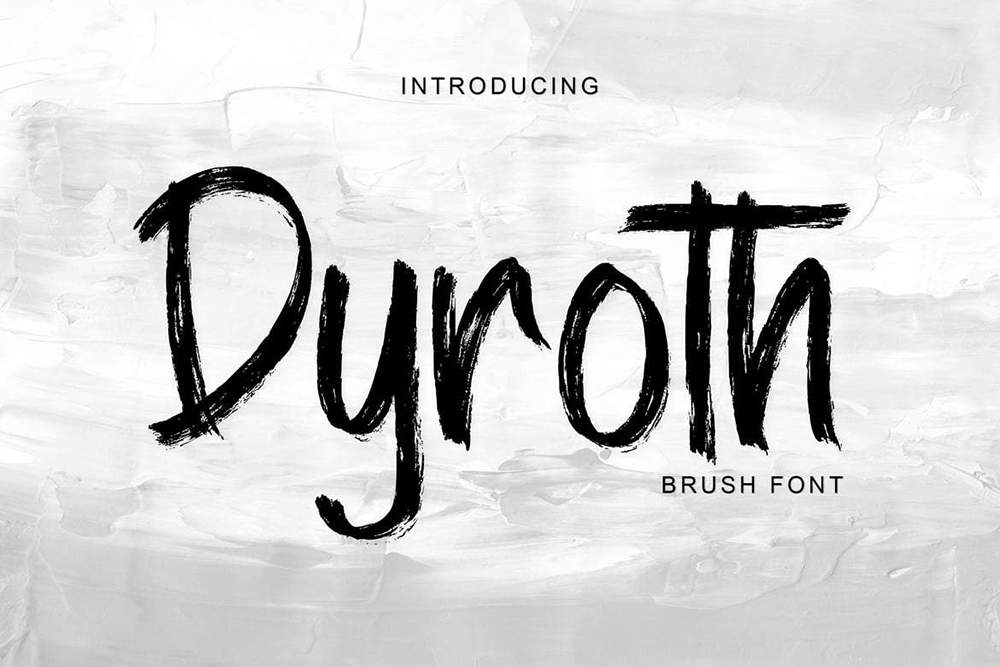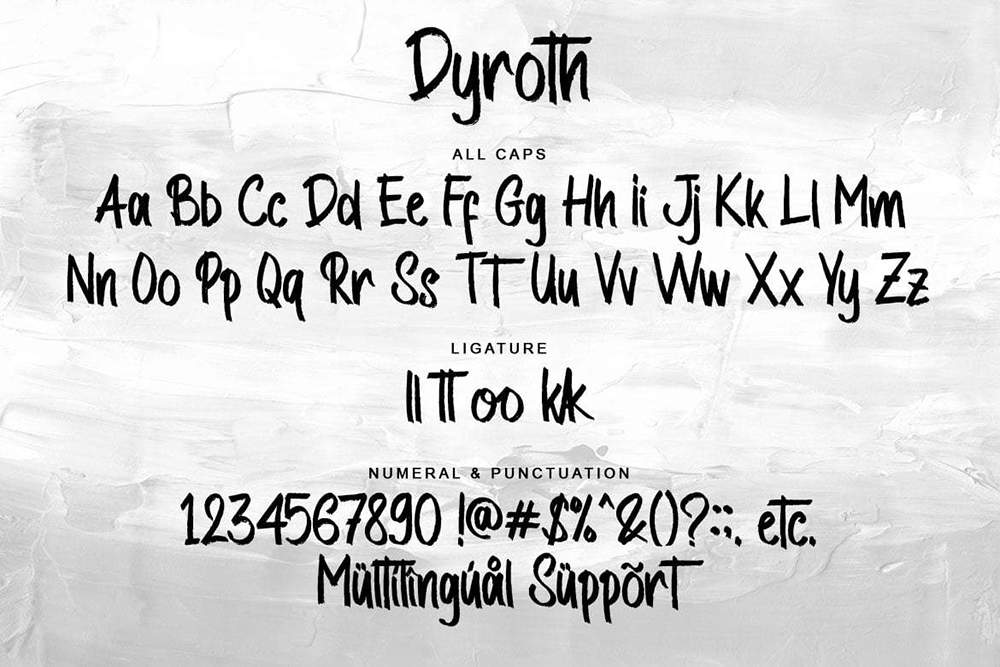
فونت پرمیوم و انگلیسی Dyroth Font یک فونت قلممو است که با حروف بزرگ و کوچک استاندارد، اعداد، علائم نگارشی، لیگاتور و پشتیبانی چندزبانه ارائه میشود. فونت Dyroth بهترین انتخاب برای برندسازی، لوگو، ماکت تیشرت، تبلیغات دیجیتال، نقل قول و غیره است. این فونت برای تمام نیازهای طراحی شما بهترین عملکرد را دارد.
مزایای استفاده از فونت لاتین Dyroth چیست؟